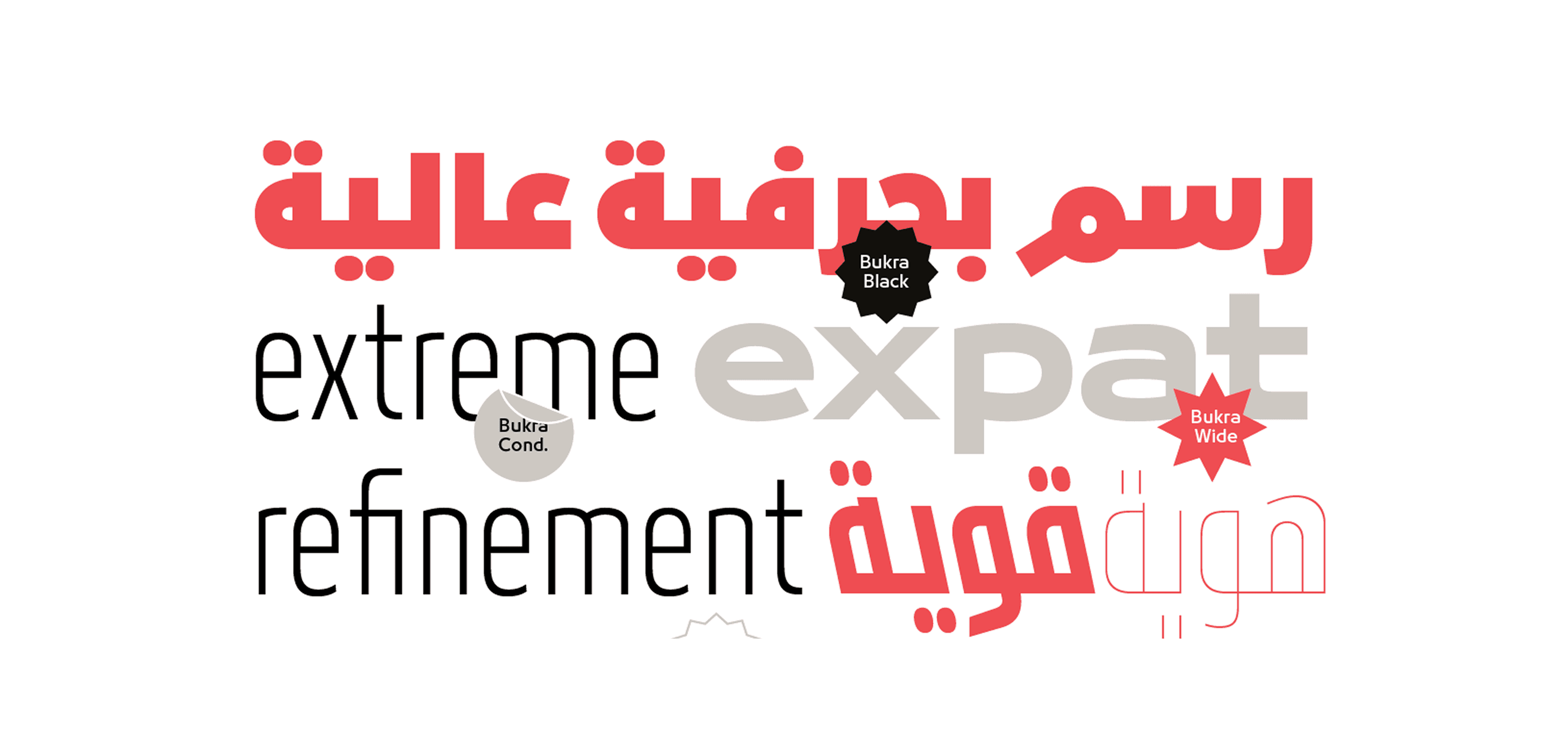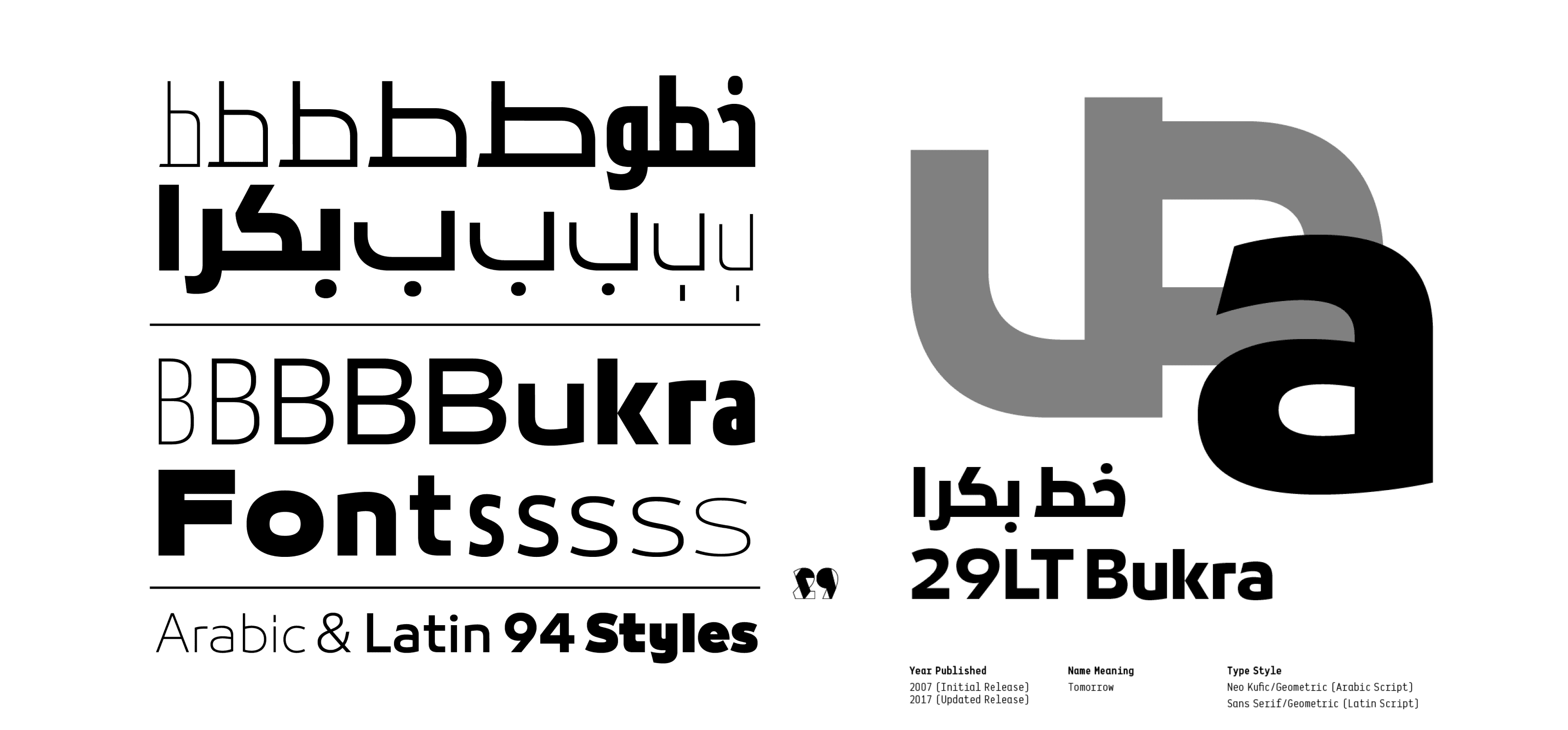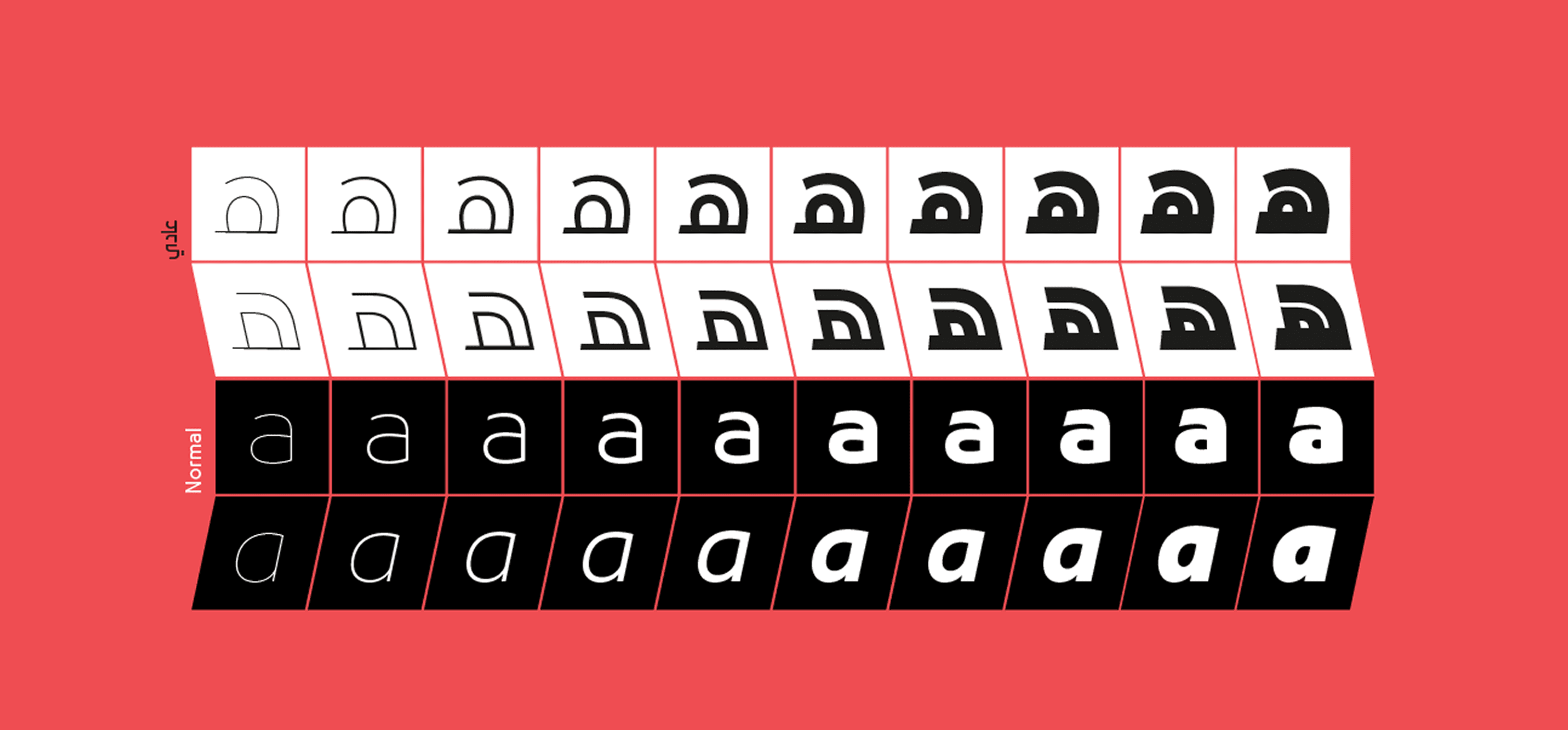
يأتي خط "بكرا" بتصميم هندسي عصري يجمع بين الصلابة والوضوح، ما يجعله مثاليًا للعناوين، الشعارات، والنصوص التحريرية الحديثة. يتميّز بتوازن بصري عالي بين الخط العربي واللاتيني، مما يجعله مناسبًا تمامًا للمشاريع ثنائية اللغة.
يحتوي الخط على عدد كبير من الأنماط والأوزان، ويتضمن خصائص متقدمة مثل تشكيل الحروف، الربطات القياسية، الرموز، والأرقام، مما يجعله ملائمًا لتطبيقات التحرير الرقمي والطباعة التقليدية على حد سواء.
يأتي خط "بكرا" بتصميم هندسي عصري يجمع بين الصلابة والوضوح، ما يجعله مثاليًا للعناوين، الشعارات، والنصوص التحريرية الحديثة. يتميّز بتوازن بصري عالي بين الخط العربي واللاتيني، مما يجعله مناسبًا تمامًا للمشاريع ثنائية اللغة.
يحتوي الخط على عدد كبير من الأنماط والأوزان، ويتضمن خصائص متقدمة مثل تشكيل الحروف، الربطات القياسية، الرموز، والأرقام، مما يجعله ملائمًا لتطبيقات التحرير الرقمي والطباعة التقليدية على حد سواء.
يأتي خط "بكرا" بتصميم هندسي عصري يجمع بين الصلابة والوضوح، ما يجعله مثاليًا للعناوين، الشعارات، والنصوص التحريرية الحديثة. يتميّز بتوازن بصري عالي بين الخط العربي واللاتيني، مما يجعله مناسبًا تمامًا للمشاريع ثنائية اللغة.
يحتوي الخط على عدد كبير من الأنماط والأوزان، ويتضمن خصائص متقدمة مثل تشكيل الحروف، الربطات القياسية، الرموز، والأرقام، مما يجعله ملائمًا لتطبيقات التحرير الرقمي والطباعة التقليدية على حد سواء.